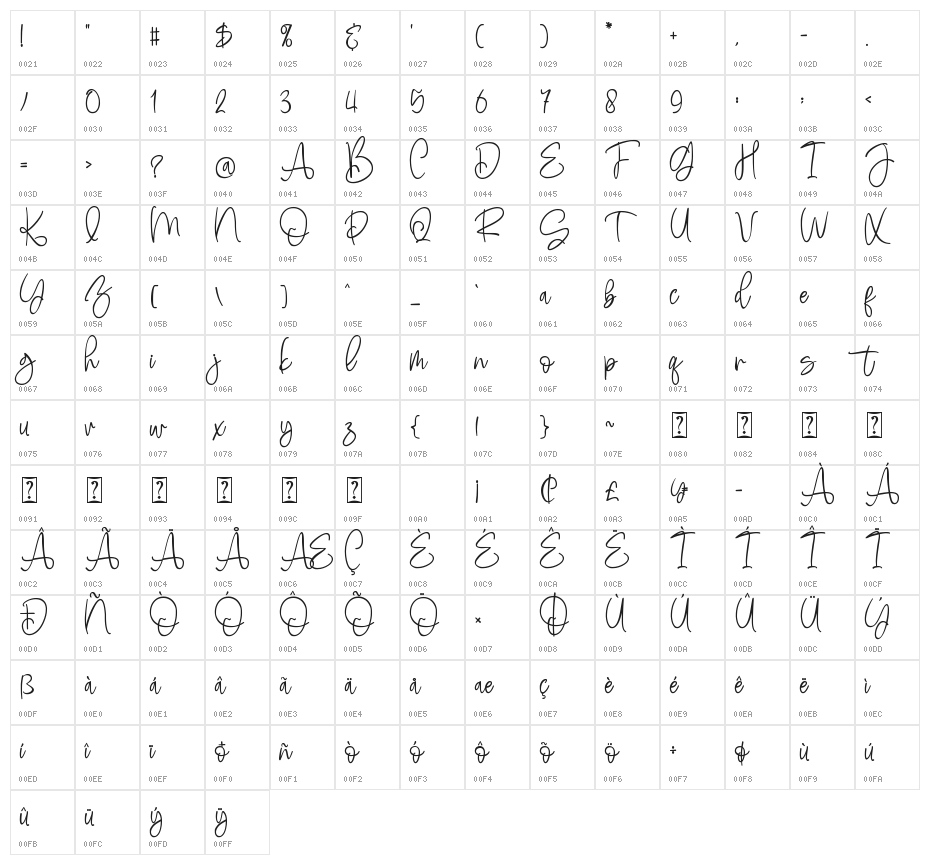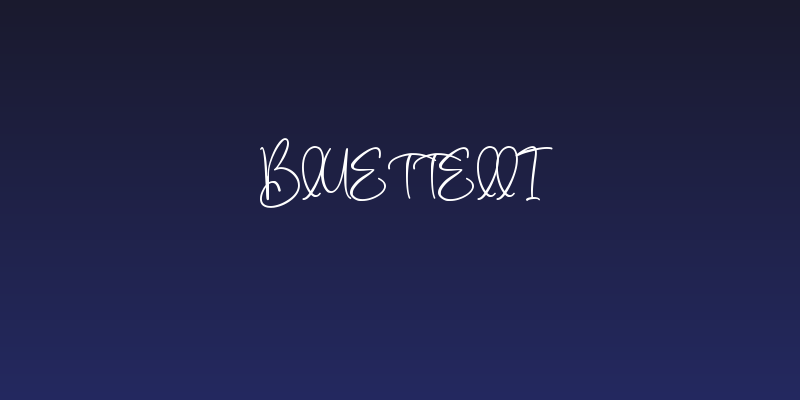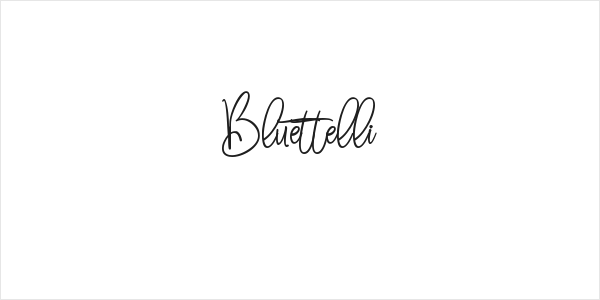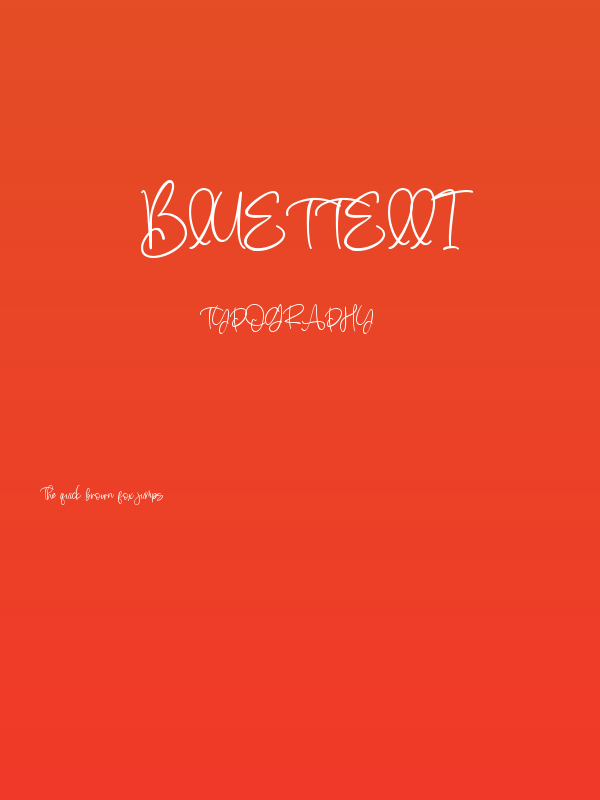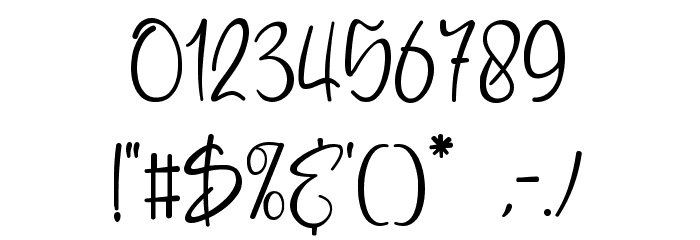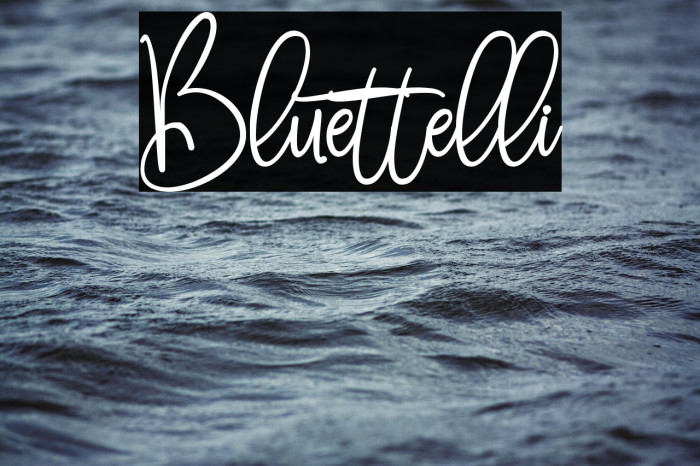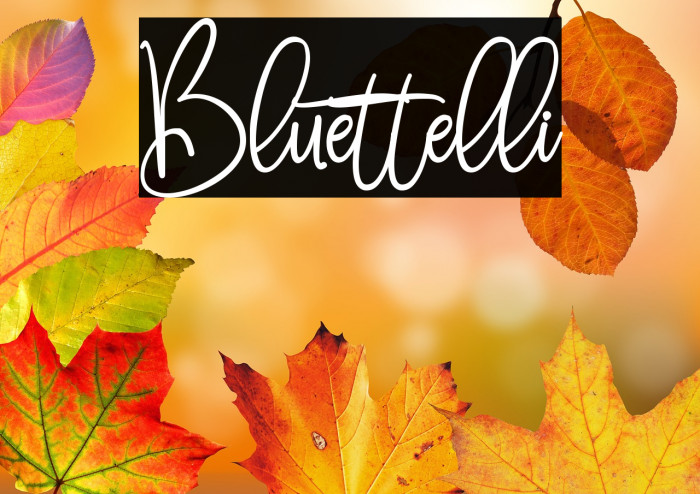
Bluettelli Font
| 全体的なスタイル | Modern, Whimsical |
| 用途 | Headlines, Logos, Invitations |
| おすすめプロジェクト | Ideal for greeting cards, invitations, personal branding, and creative projects requiring a personal touch. |